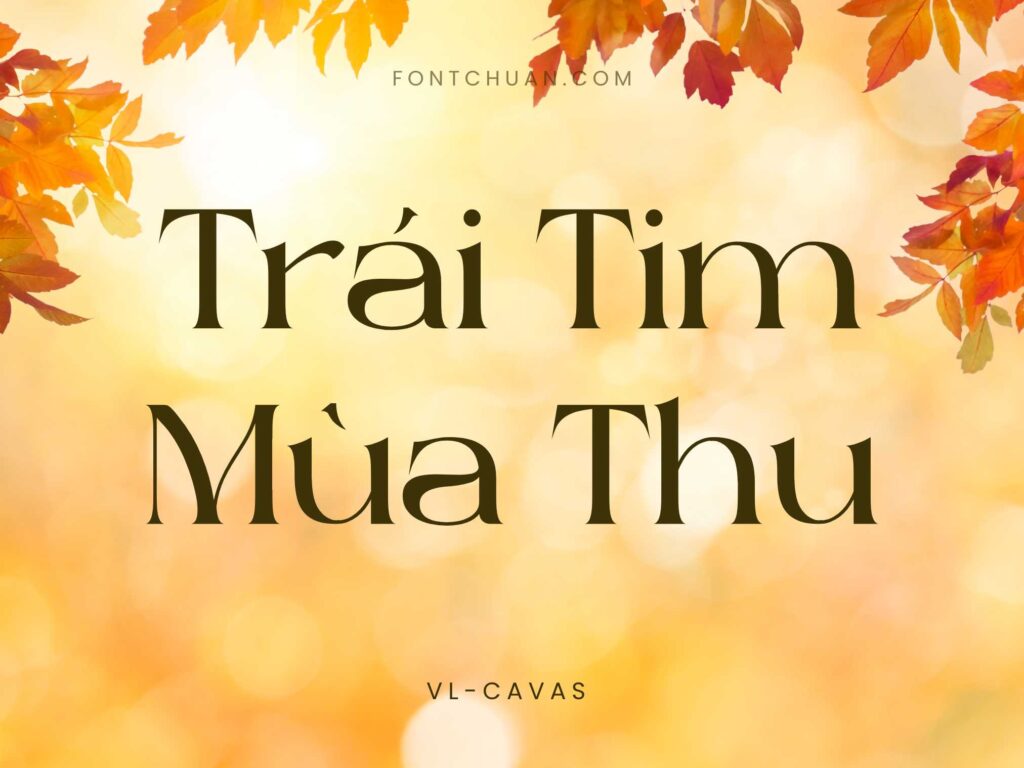
Font VL Cavas Việt Hóa
Tác giả Font: Ekayasa Ekayasa
Việt hóa bởi: Font Việt Linh
VL-Cavas là một phông chữ serif mang phong cách sang trọng và tinh tế, được thiết kế bởi Ekayasa. Phông chữ này có các đường nét mềm mại và uốn lượn, tạo nên sự hiện đại và cuốn hút trong các thiết kế. VL-Cavas đã được Việt hóa bởi Việt Linh, hỗ trợ đầy đủ các ký tự tiếng Việt, giúp người dùng dễ dàng sử dụng trong các dự án sáng tạo. Phông chữ này được thành viên Font Chuẩn sưu tầm và đăng tải nhằm phục vụ nhu cầu thiết kế đa dạng.
Với thiết kế thanh lịch và rõ ràng, VL-Cavas phù hợp cho các ứng dụng như tiêu đề, văn bản dài, thiết kế logo và các ấn phẩm in ấn. Trong lĩnh vực sự kiện, phông chữ này có thể được sử dụng trong các dịp như lễ cưới, hội nghị và các sự kiện văn hóa. Ngoài ra, VL-Cavas cũng thích hợp cho các ngành nghề như quảng cáo, giáo dục và công nghệ.